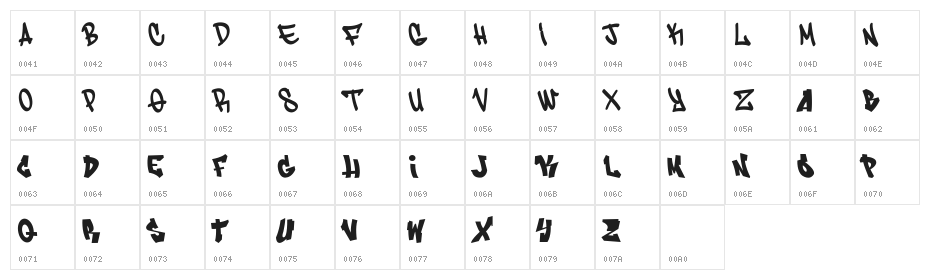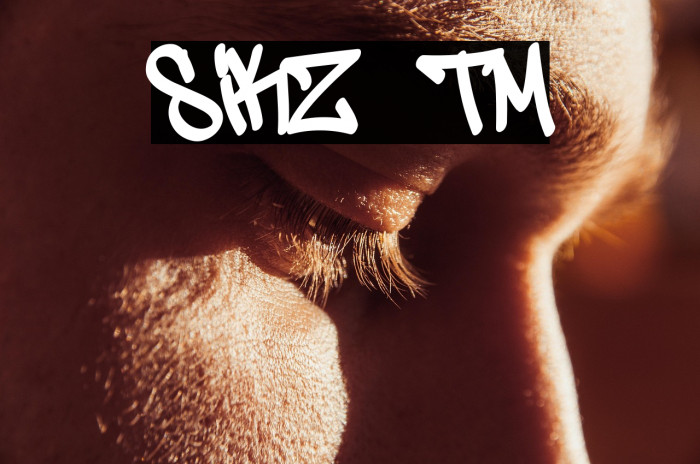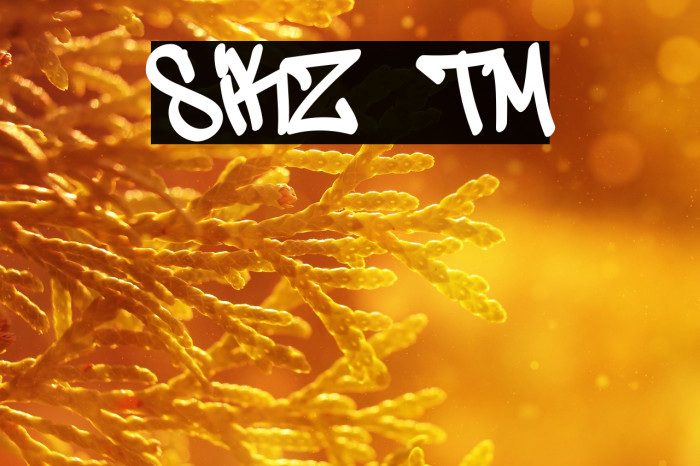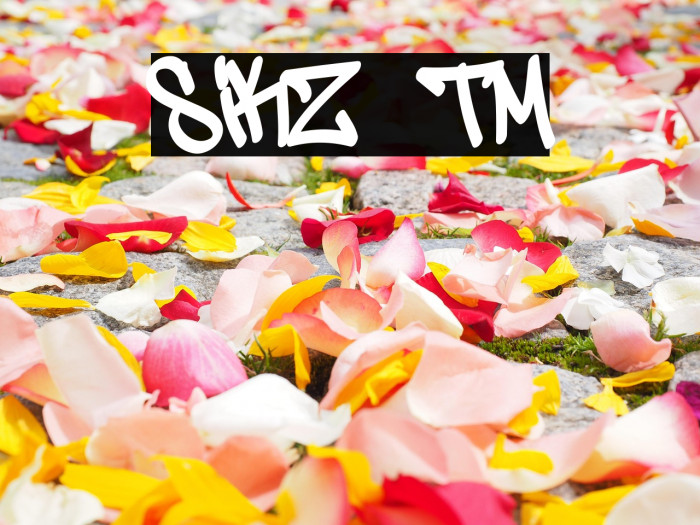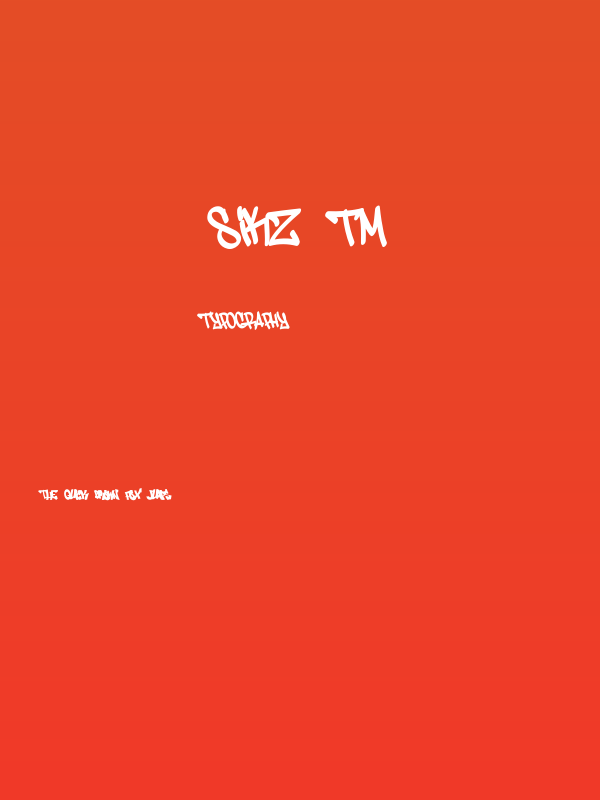
SIKZ TM Font
| Stile generale | Urban, Graffiti, Bold |
| Progetti proposti | Ideal for street art designs, urban-themed posters, music album covers, and edgy branding projects. |